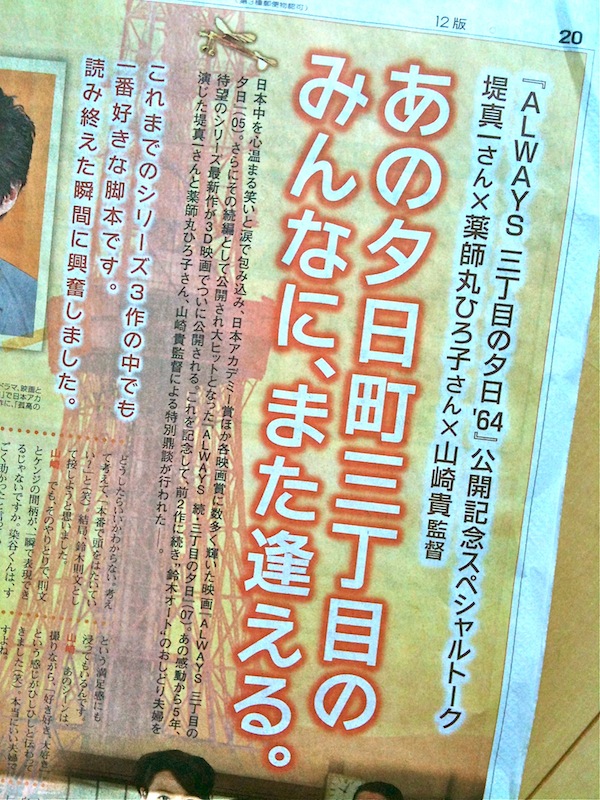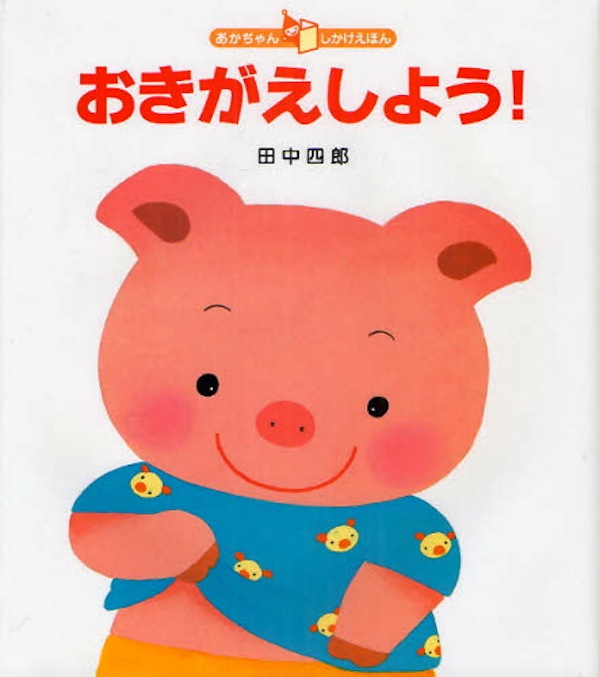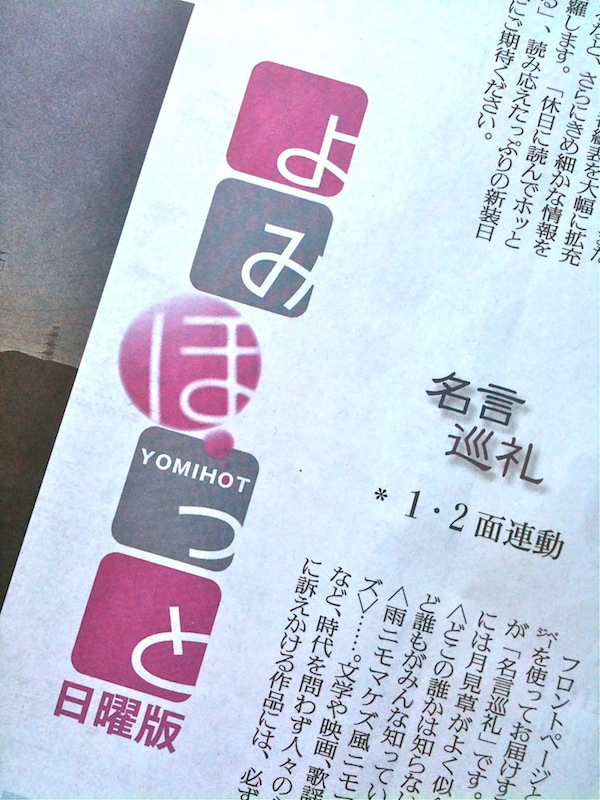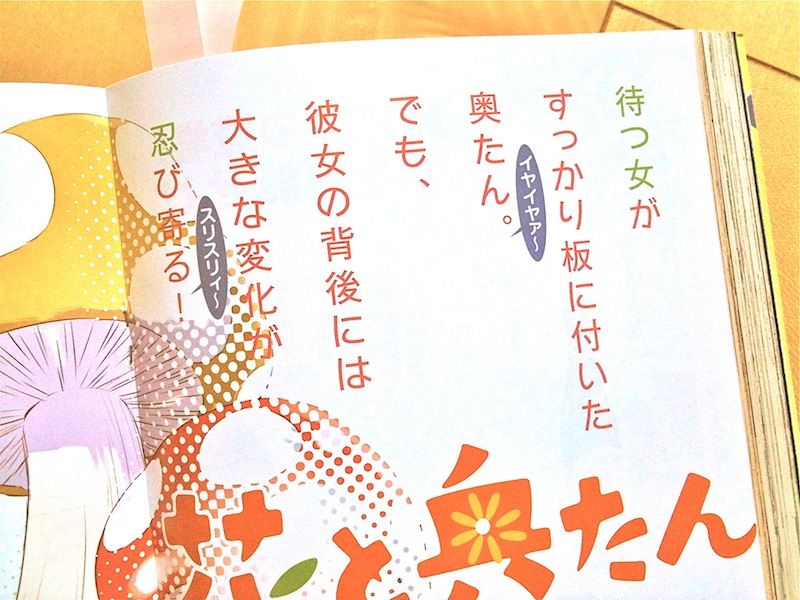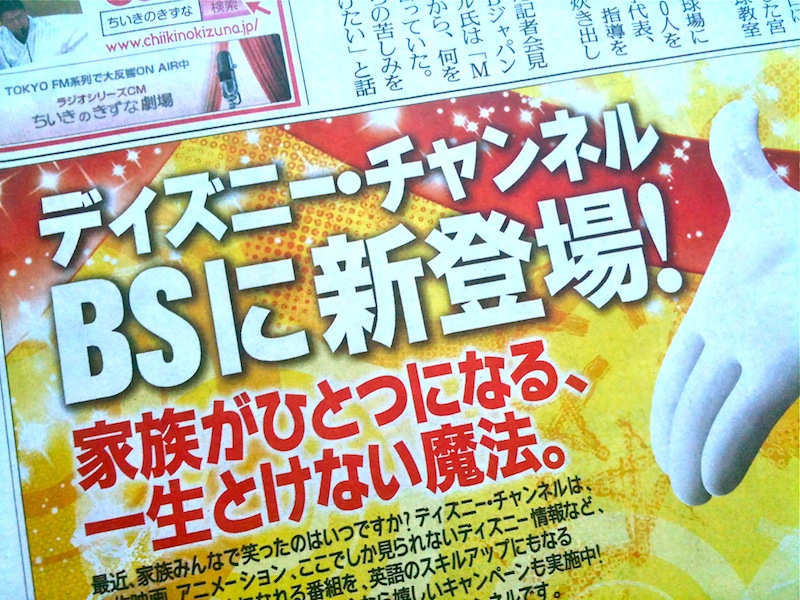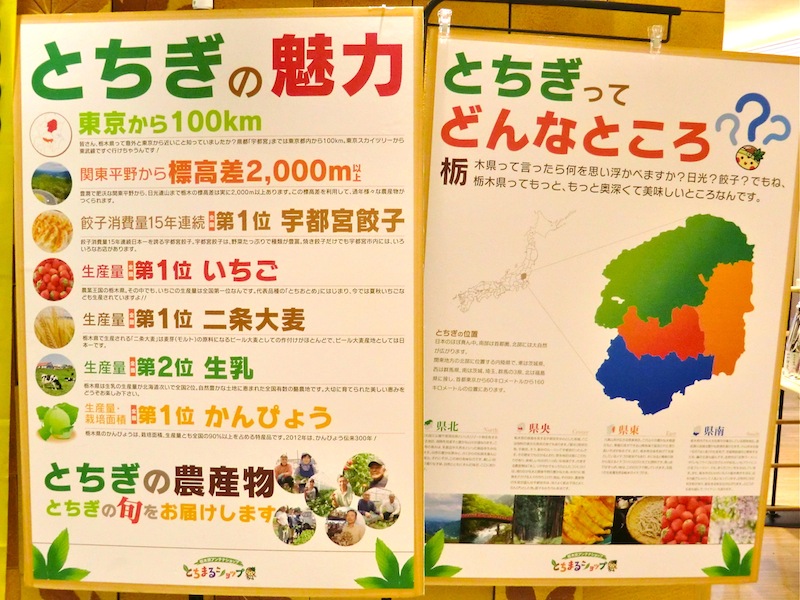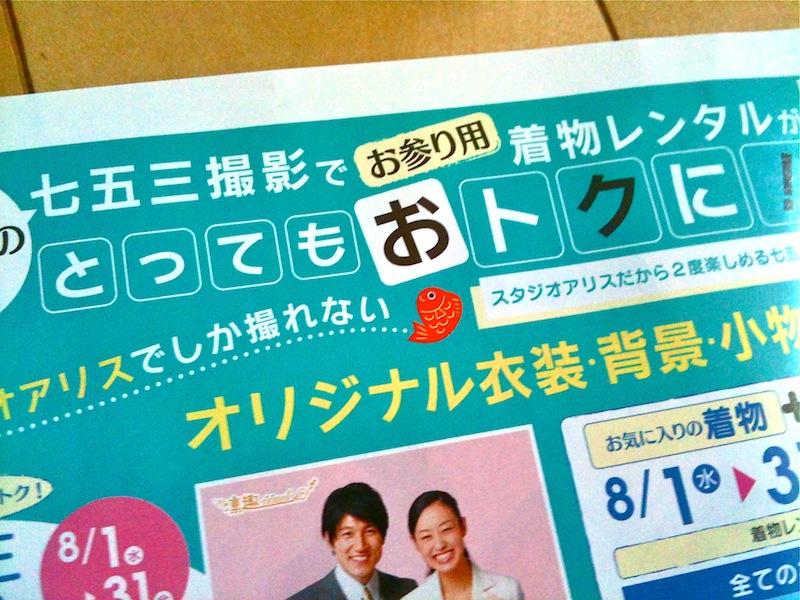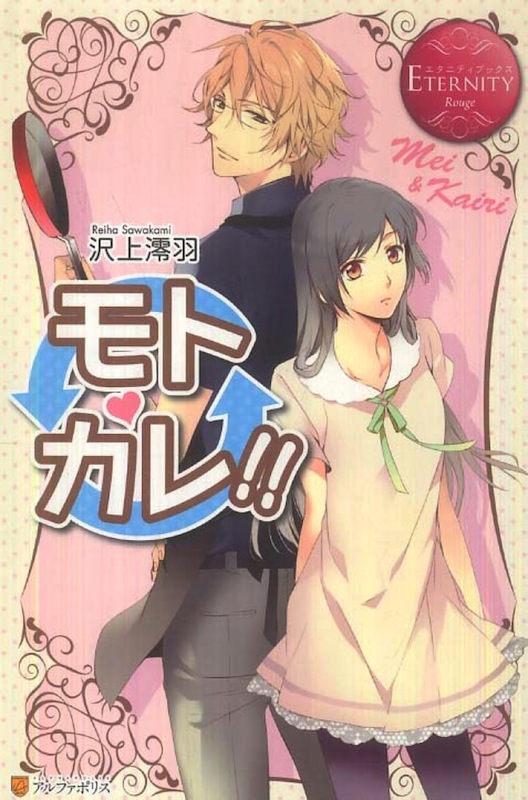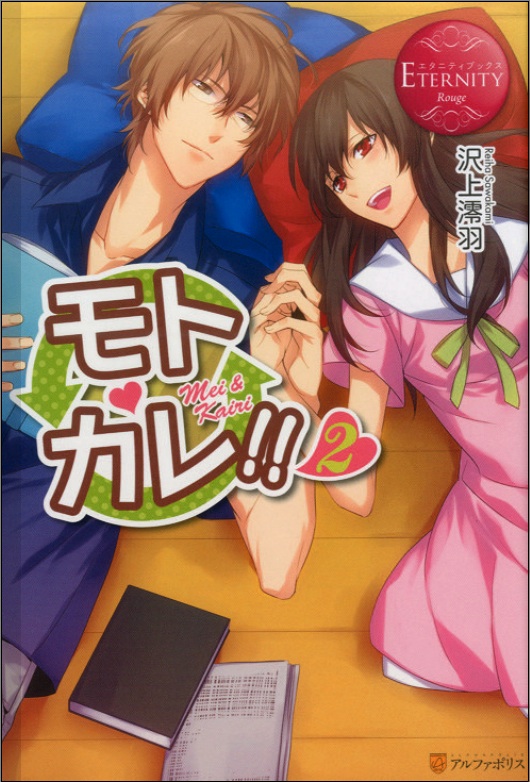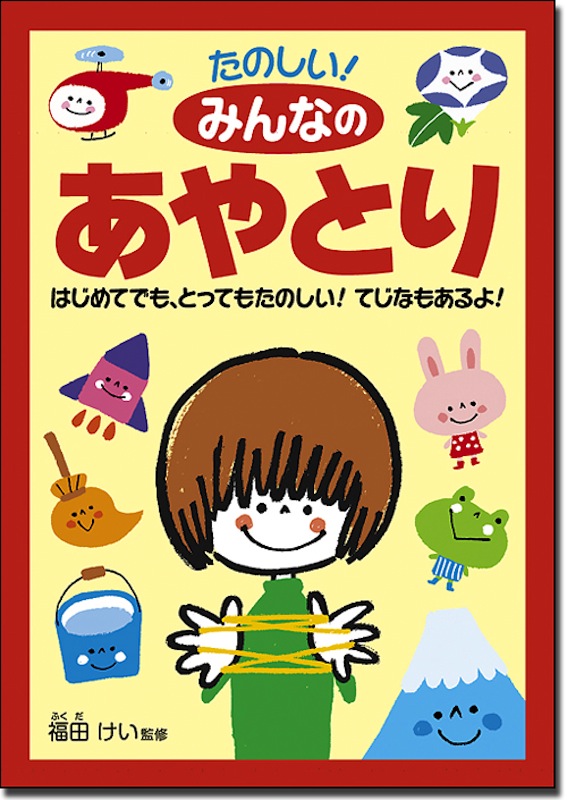
公園のロゴ  さとうゆたか  2013年12月18日(水) 16:38
明治神宮外苑にある幼児用の公園、にこにこパーク。
絵本の表紙  さとうゆたか  2013年12月18日(水) 16:36
書名:めくりをあけてあそぼうよ!
著者:ステラ・バゴット、きたむらまさお
発行:大日本絵画
テレビ番組  さとうゆたか  2013年9月22日(日) 10:45
テレビ東京の「ドラGO!」。
もう1点。
なにかと話題になった本  さとうゆたか  2013年9月9日(月) 17:03
これは新聞広告。
こちらは、デジタルフォントのわんぱく書体が使われているが…。
こちらは文庫版の表紙。
写植時代のわんぱく書体が使われている。
和光堂のおやつ  さとうゆたか  2013年8月27日(火) 16:40
赤ちゃん用のおやつです。
これも同じシリーズです。
これも…。
しつこいけど、もう1点。
旅先で  さとうゆたか  2013年8月12日(月) 17:01
東北方面の観光バスに貼られたステッカー。
こちらは交通マナー看板。
ローソンストア100の貼り紙で…  takumi  2013年7月8日(月) 18:37
『ローソンストア100』の貼り紙で、わんぱく書体が使われていました。
他社のUDフォントと組み合わせているのでしょうか(イマイチ…)。
あちこちの小さな文字にも使われていますね。
カップめんの「かやく」の袋  takumi  2013年5月25日(土) 12:25
インスタントラーメンの「かやく」の袋でわんぱく書体が使われていました。
いつも漢字とひらがな・カタカナが一緒になった使用例ばかり探していたので、本来の「かな」だけの使用例は新鮮ですね。
お、「わんぱくベビー」書体ですね。
デジタルフォント化されてませんから、今では珍しい使用例です。
Webサイトのロゴ  さとうゆたか  2013年5月2日(木) 9:49
上野動物園からライブ映像を配信中。
関西テレビの番組でわんぱくルイカ?  takumi  2013年4月28日(日) 21:52
最近、関西テレビのバラエティ番組『ウラマヨ!』で、わんぱく書体が使われるようになりました。
自信はありませんが、たぶん、『わんぱくルイカ』だと思います。
わんぱく書体はかわいらしい感じなのに真面目でしっかりした(?)デザインなので、幅広く使えて便利ですね♪
確かに「わんぱくルイカ」のようです。
ウェイトは08くらいでしょうか。